北京2022冬奥会、冬残奥会会徽正式发布
冬奥会会徽“冬梦”:以“冬”字为灵感来源
名为“冬梦”的冬奥会会徽以汉字“冬”为灵感来源,运用中国书法的艺术形态,将厚重的东方文化底蕴与国际化的现代风格融为一体,呈现出新时代的中国新形象、新梦想,传递出新时代中国为办好北京冬奥会,圆冬奥之梦,实现“三亿人参与冰雪运动”目标,圆体育强国之梦,推动世界冰雪运动发展,为国际奥林匹克运动做出新贡献的不懈努力和美好追求。
会徽图形上半部分展现滑冰运动员的造型,下半部分表现滑雪运动员的英姿。中间舞动的线条流畅且充满韵律,代表举办地起伏的山峦、赛场、冰雪滑道和节日飘舞的丝带,为会徽增添了节日喜庆的视觉感受,也象征着北京冬奥会将在中国春节期间举行。
会徽以蓝色为主色调,寓意梦想与未来,以及冰雪的明亮纯洁。红黄两色源自中国国旗,代表运动的激情、青春与活力。
在“BEIJING 2022”字体的形态上汲取了中国书法与剪纸的特点,增强了字体的文化内涵和表现力,也体现了与会徽图形的整体感和统一性。
冬残奥会会徽“飞跃”:展现汉字“飞”的动感和力度
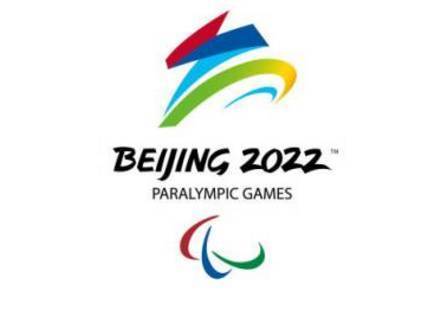
冬残奥会会徽设计秉承展现举办地文化、体现以运动员为中心的理念,将中国书法艺术与冬残奥会体育运动特征结合起来。设计展现了汉字“飞”的动感和力度,巧妙地幻化成一个向前滑行、冲向胜利的运动员,同时形象化地表达了轮椅等冬残奥会特殊运动器械形态。上半部分线条刚劲曲折,下半部分柔美圆润,寓意运动员经过顽强拼搏、历经坎坷最终达到目标获得圆满成功。会徽展现了运动员不断飞跃,超越自我,奋力拼搏,激励世界的冬残奥精神。
会徽图形整体充满了昂扬向上之激情,奋进飞跃之动感,色彩丰富,构图完美,象征并激发运动员以坚强的意志作为精神的翅膀,在冬残奥赛场上放飞青春梦想!